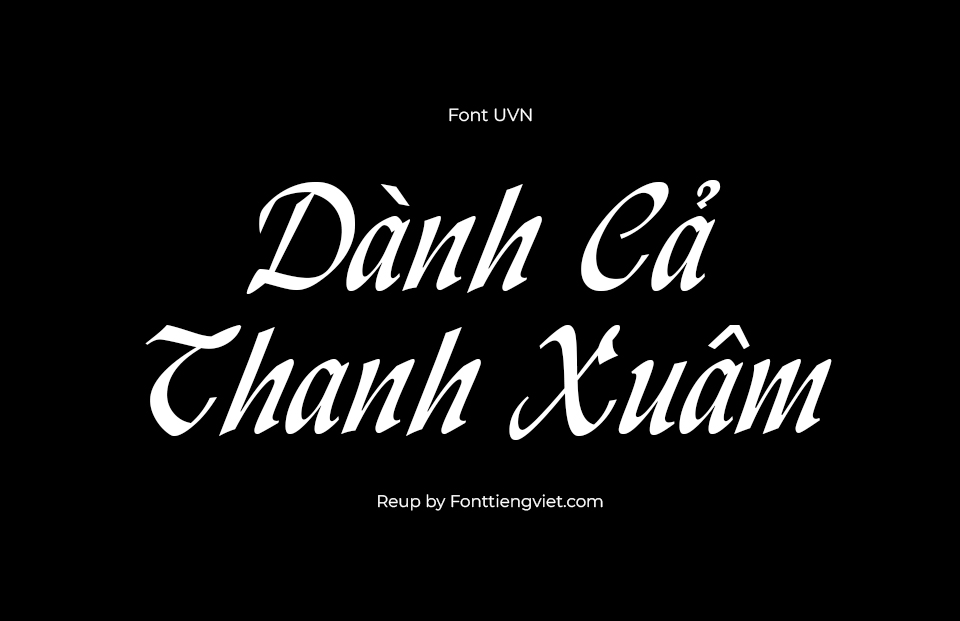
Font Việt Hóa UVN Ly Do
Font Việt Hóa UVN Ly Do – Lựa chọn hoàn hảo cho giáo dục và văn phòng
Giới thiệu về Font Việt Hóa UVN Ly Do
Trong thiết kế đồ họa và soạn thảo văn bản tại Việt Nam, việc tìm kiếm một bộ Font Chữ vừa mang nét truyền thống vừa đảm bảo tính hiện đại là điều vô cùng cần thiết. Font Việt Hóa UVN Ly Do nổi lên như một giải pháp tối ưu, đáp ứng đầy đủ các tiêu chuẩn về thẩm mỹ và kỹ thuật cho người dùng Việt. Được phát triển dựa trên bảng mã Unicode chuẩn quốc tế, bộ font này giúp người dùng dễ dàng gõ tiếng Việt có dấu mà không lo xảy ra lỗi hiển thị hay mất ký tự đột ngột.
Đặc điểm nổi bật của Font Việt Hóa UVN Ly Do
Lý do khiến bộ font này được ưa chuộng nằm ở những đường nét thanh mảnh nhưng vô cùng dứt khoát. Font Việt Hóa UVN Ly Do sở hữu cấu trúc ký tự rõ ràng, khoảng cách giữa các chữ cái được căn chỉnh tỉ mỉ, giúp việc đọc văn bản dài trở nên dễ dàng và không gây mỏi mắt. Đây là một trong những lựa chọn hàng đầu cho các tài liệu giảng dạy, bài thi hay các ấn phẩm truyền thông học đường nhờ phong cách trang nhã và chuyên nghiệp.
Ứng dụng thực tế của Font Việt Hóa UVN Ly Do trong đời sống
Với sự linh hoạt cao, Font Việt Hóa UVN Ly Do không chỉ giới hạn trong môi trường sư phạm mà còn ứng dụng rộng rãi trong thiết kế menu, thiệp mời và bìa sách. Người dùng có thể tùy biến font trong các phần mềm phổ biến như Microsoft Word, Photoshop hay Illustrator một cách mượt mà. Khả năng tương thích tốt trên nhiều nền tảng giúp bộ font này trở thành công cụ đắc lực cho cả giáo viên và sinh viên khi thực hiện các dự án sáng tạo.
Kết luận về bộ Font Việt Hóa UVN Ly Do